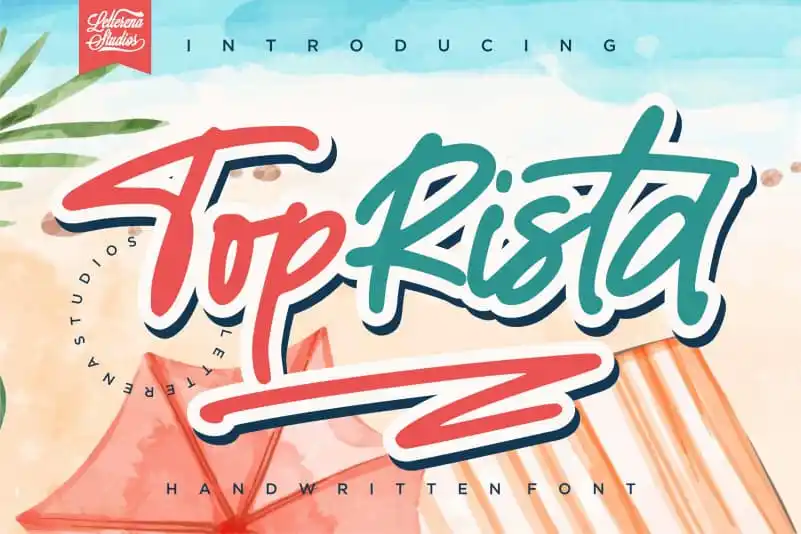
TopRista – Unique Handwritten Font – Download Grátis
A “TopRista” é uma elegante e única fonte feita especialmente para quem aprecia o encanto do escrita à mão livre. Criada pelo designer letterenastudios, esta fonte única oferece um toque pessoal aos textos digitais que pode personalizar suas publicações ou sites com estilo. Essa fonte é perfeita para aqueles que buscam algo diferente e mais autêntico em seu design visual. Com seu traço delicado e nuances únicas, a “TopRista” é ideal tanto para anúncios de marketing quanto para pequenos projetos pessoais. Como menciona no documento original, esta fonte deve ser usada apenas para fins pessoais não comerciais. Ela traz um toque especial que vai destacar seu design em qualquer plataforma digital onde você a use.